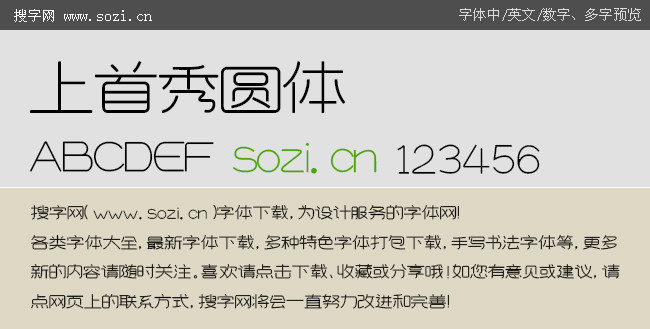
上首秀圓體
搜字網(wǎng)給大家提供一款上首秀圓體中文字體下載,上首秀圓體,字體風(fēng)清新秀麗,筆畫瘦長,轉(zhuǎn)角圓潤,是此套字庫的亮點(diǎn)。字庫整體特征柔和、圓潤,具有現(xiàn)代感十足,適用于搭配標(biāo)志、廣告標(biāo)語、商業(yè)廣告等高端屬性。